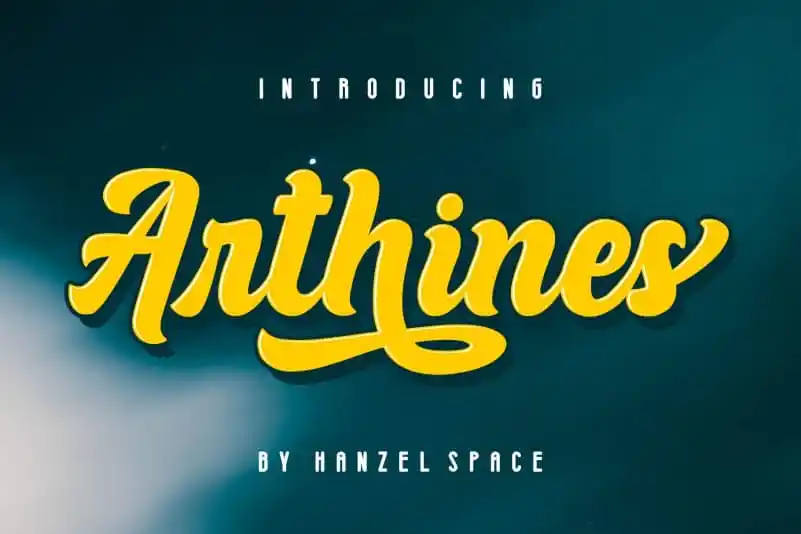
Arthines Script Font – Download Grátis
A Arthines Script Font é uma fonte que se destaca pela sua elegância única e naturalidade fresca. Ela surge dos arredores da Hanzel Space inspirada no estilo de escrita livre, com um moderno design que convida a criar letras digitais fáceis e intuitivas para diversos usos. O designer da 99designs trabalhou em uma fonte versátil que inclui muitas alternativas de caracteres minúsculos e maiúsculos, ligaturas e configurações para formar as letras inicial e terminal de forma eficiente. É perfeita tanto para design de logotipos como para posters digitais ou arte em letra, também é ideal para criação de marcas e assinaturas, oferecendo uma abordagem clara e atraente para qualquer projeto que exija um toque natural e moderno.